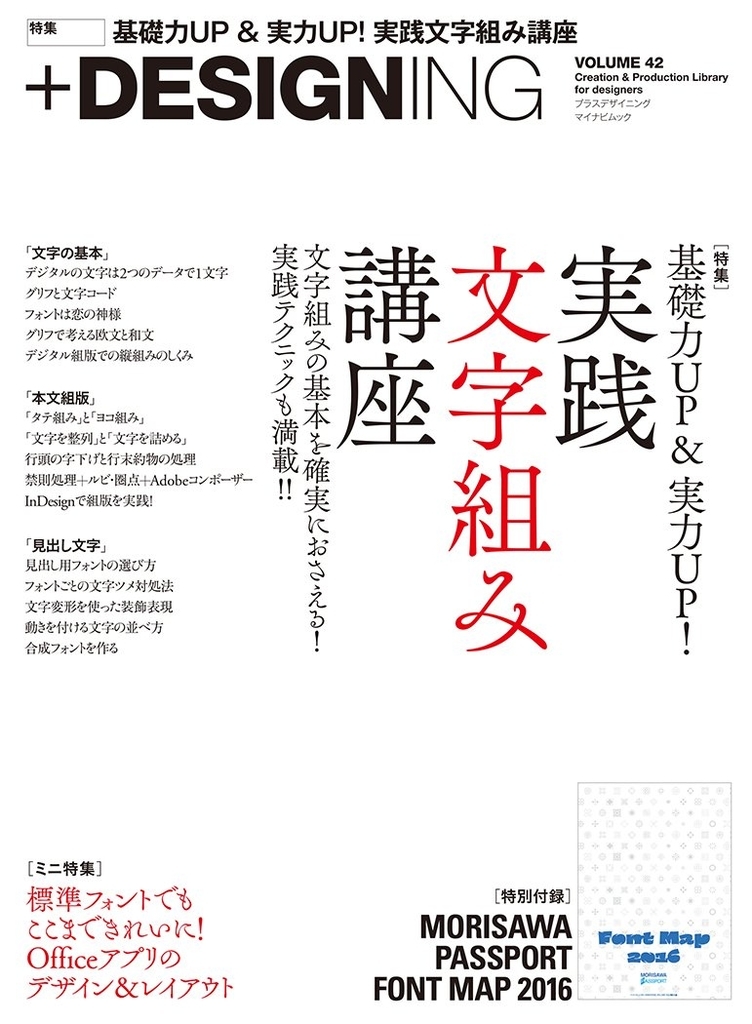
AXISラウンド 100
AXIS Font ファミリーの新書体「AXIS ラウンド 100」が2017年3月2日に発売を開始した。2017年01月19日に発売を開始した新たなAXIS Font ファミリー「AXISラウンド 50」に続く形となる。
太さもAXIS Fontベーシックと同じく、ウルトラライト、エクストラライト、ライト、ミディアム、ボールド、ヘヴィの7種類に対応しており、AXISラウンド 100のリリースにより、3種のAXISフォントの使い分けが可能になった。
AXISラウンド 100の特徴
「AXISラウンド 50」がシャープな輪郭にわずかな丸み帯びた特徴があるのに対し、「AXISラウンド 100」では通常の丸ゴシックとは異なり、内径を丸めずにサンセリフのシャープさを遺しているのが特徴となっている。
巻頭ページでタイププロジェクト特集「+DESIGNING VOLUME 42」
「+DESIGNING VOLUME 42」では巻頭ページでタイププロジェクトの特集記事が組まれている。
タイププロジェクトTP明朝使用作品「アルドノア・ゼロ」
タイププロジェクトのフォントといえば、デジタル時代の横書き明朝体「TP明朝」がSFアニメ「アルドノア・ゼロ」に使用されていたのが印象的だった。